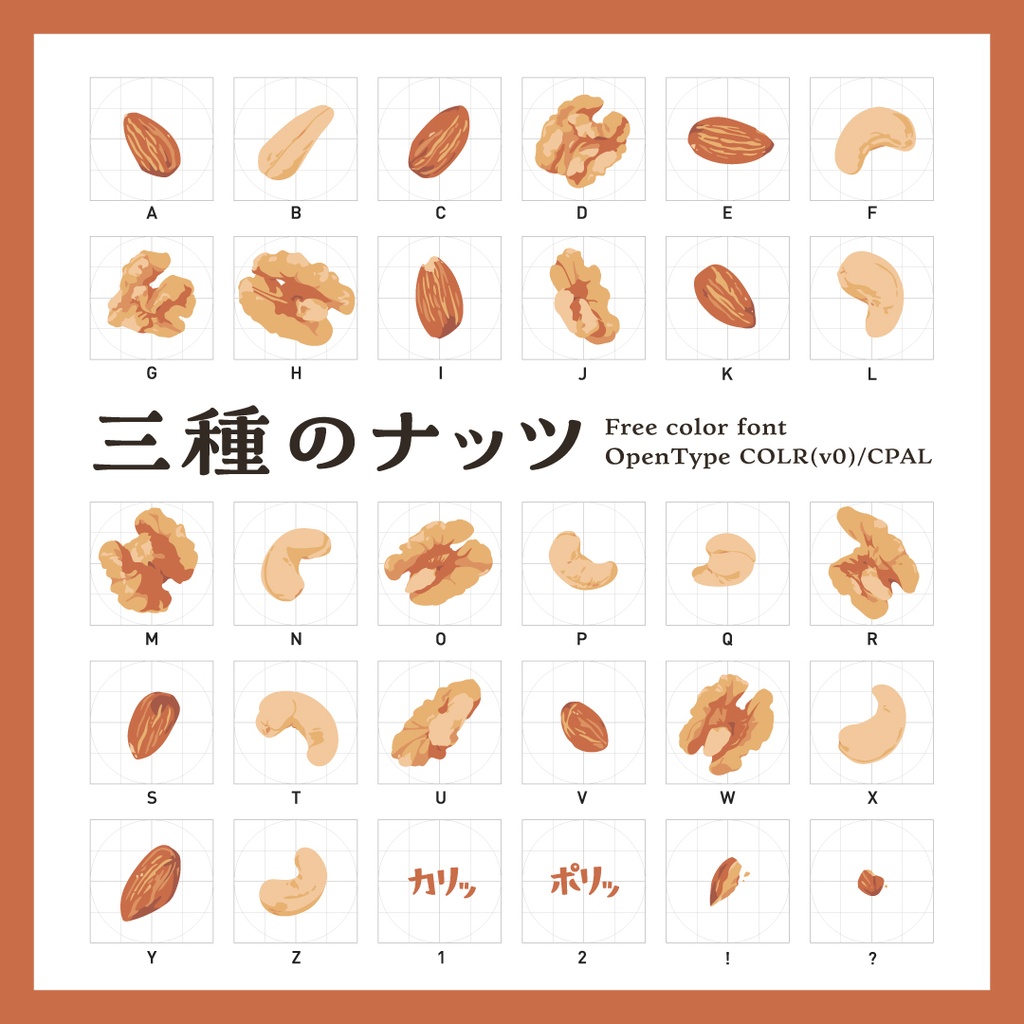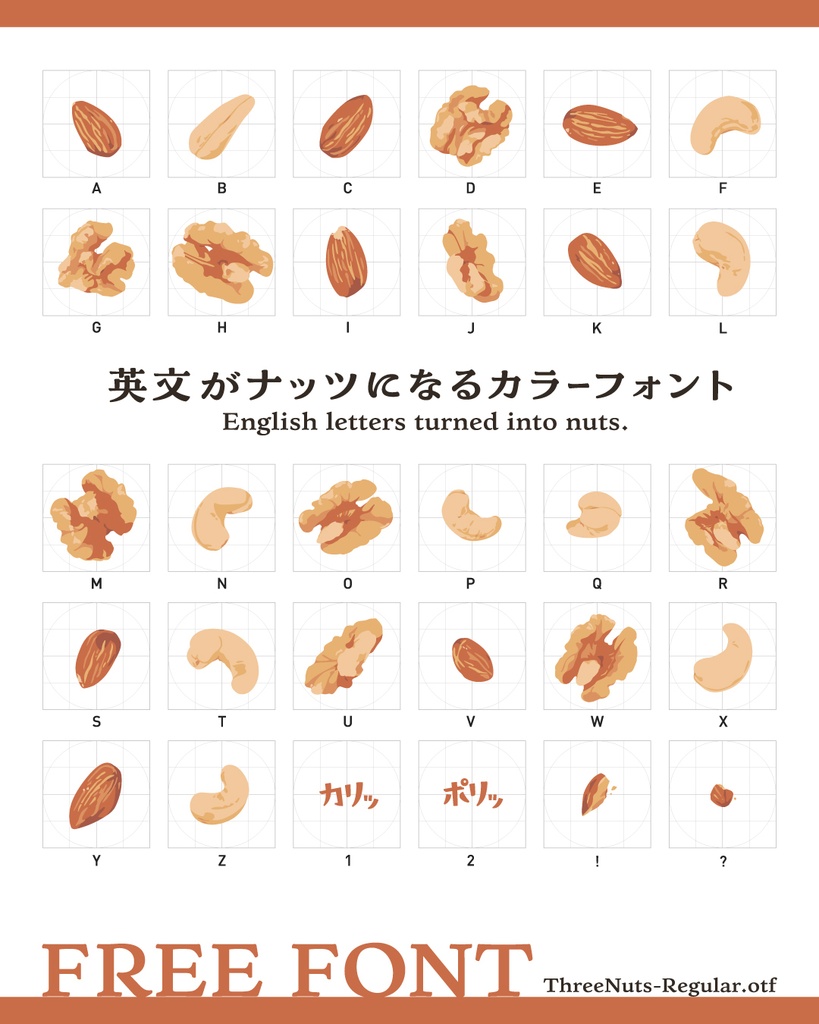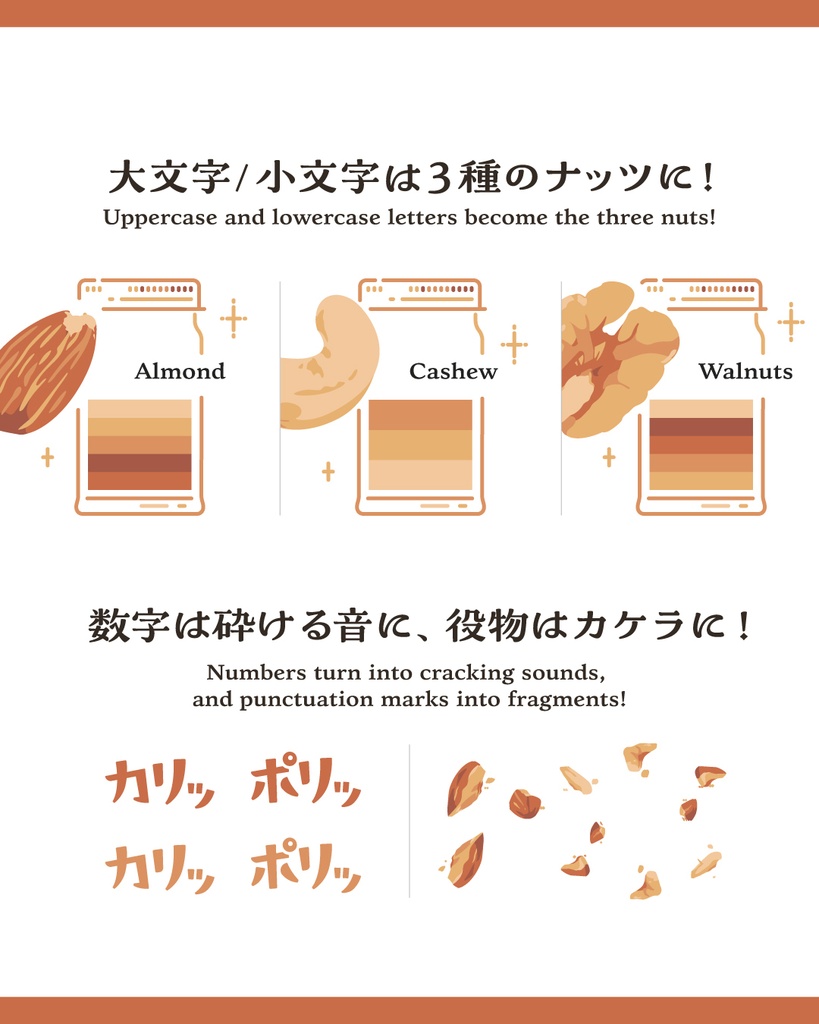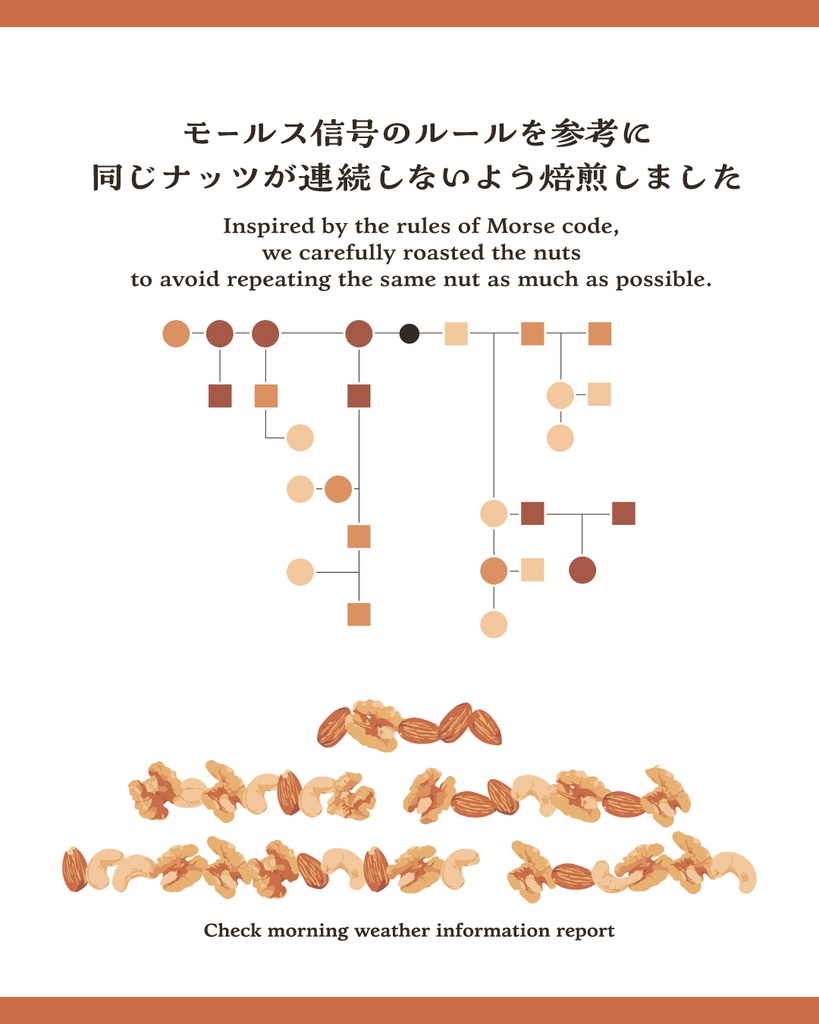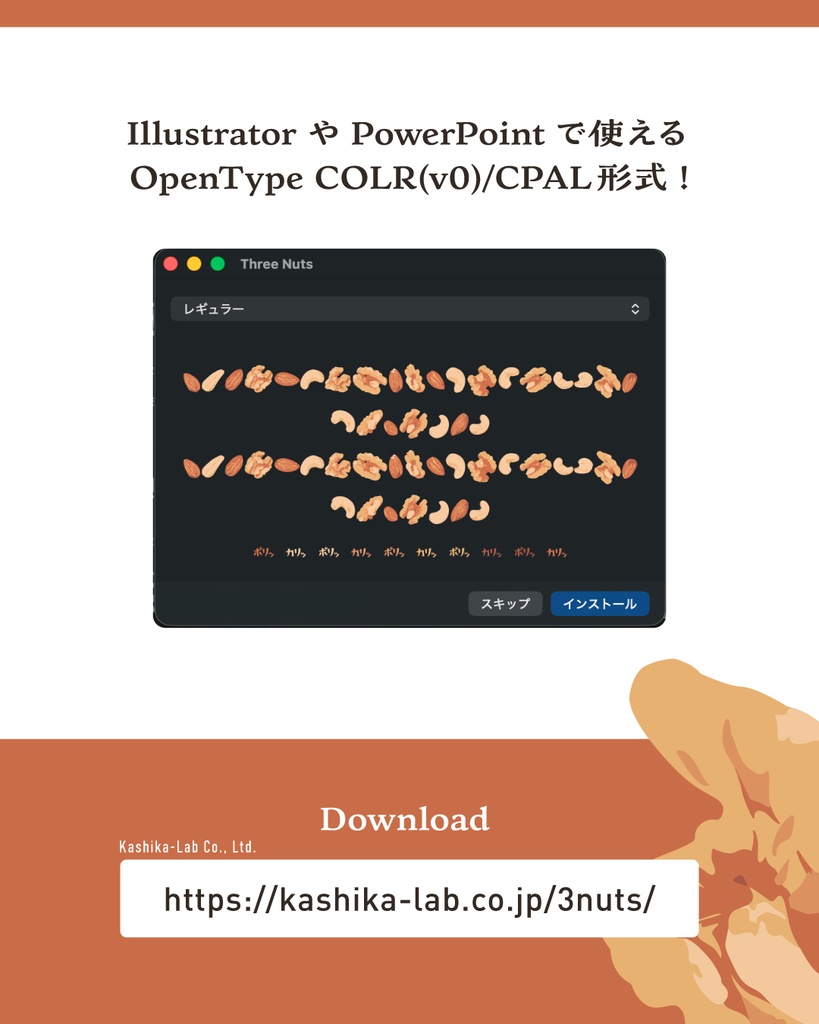
三種のナッツ(絵文字カラーフォント)
「3種のナッツ(Three Nuts Emoji)」は、 英語のテキストをナッツに置き換えて表示できる、絵文字カラーフォントです。 キーボードを自由に叩いたり、好きな英文を本フォントに変換したりすることで、 山盛りのナッツを描くことができます。 ■ フォントデータ形式 OpenType(COLR(v0)/CPAL形式) ※ スマートフォンの絵文字とはシステムが異なりますのでご注意ください。 ※ カラーフォント未対応のアプリでご使用の場合は、単色テキストとして表示されるか、事前に対応ソフト等で画像(PNG/SVG)化して読み込んでいただく必要があります。 ■ 動作確認 Microsoft Office(Windows/mac) ◯ Illustrator(デスクトップ版) ◯ Illustrator(iPad版) ✕(実機確認) Photoshop(デスクトップ版) ◯(実機確認) Photoshop(iPad版) ◯(実機確認) After Effects ✕(公式情報で確認) Keynote ◯(実機確認) CLIP STUDIO PAINT ✕(実機確認) Affinity(3.2以降) ◯ Chrome / Edge / Firefox ◯(COLRv0) Safari ◯(COLRv0のみ) ※COLR(v0)/CPAL形式は、色情報を保持したまま表示する特殊なフォント形式のため、環境によっては正しく表示されない場合がございます。 本フォントは無償で配布しているフリーフォントのため、個別の動作サポートについては対応いたしかねますこと、あらかじめご了承ください。 表示されないアプリケーションをご確認いただけました際は、今後の参考とさせていただきますので、マシュマロにてご報告いただけますと幸いです。 ・ご意見ご感想はこちら(マシュマロ) ■ 収録文字 ABCDEFGHIJKLMNOPQRSTUVWSYZ abcdefghijklmnopqrstuvwxyz 0123456789 ⁄.,:•;…!?·*#(){}[]-–_‘’‹› ■ ご利用について ・商用・個人利用ともにご利用いただけます。 ・絵文字フォントの形をもとに加工・変形して制作することも可能です。 ・使用報告やクレジット表記不要です。 ・当フォントを使用した書類データを共有する際には、フォントの埋め込みを処理をお忘れなく。 ■ ライセンスについて 「3種のナッツ(Three Nuts Emoji)」において、使用者がフォントライセンスを取得する必要はありません。 ■ 絵文字フォント使用許諾 フォントデータそのものの複製・改変・再配布はご遠慮ください。 このフォントに含まれる絵文字を「そのものがメインの目的となる商品(例:絵文字だけのTシャツやマグカップなど)」として商用利用することはできません。 フォントは、予告なくアップデートされる場合があります。 フォントをご利用いただいたことによって発生した機器やソフトウェアの不具合・誤作動・誤出力・ウイルス感染などについては、責任を負いかねます。 ■ 三種のナッツ特設ページ こちらからもフリーダウンロード可能です https://kashika-lab.co.jp/3nuts/